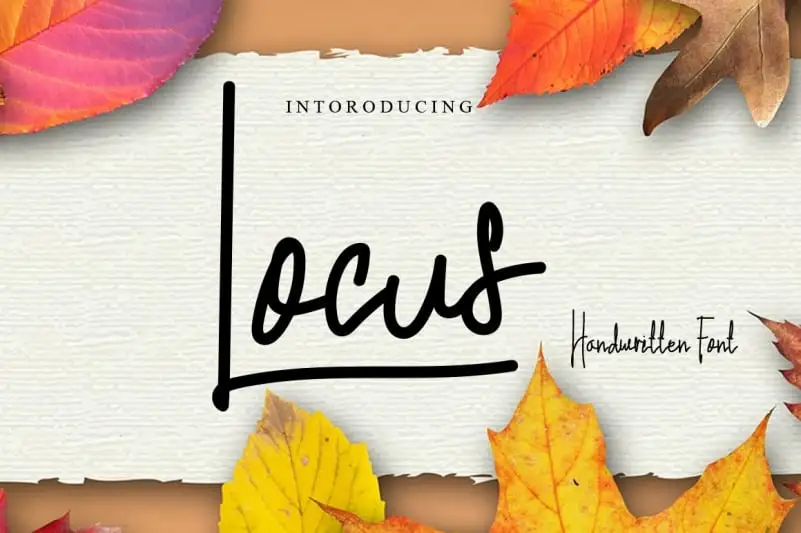
Locus Handwritten Font – Download Grátis
A Locus Handwritten Font é uma elegante escolha para aqueles que buscam uma fonte escrita a mão com um toque natural e fluído. Esta fonte é perfeitamente adaptada para ambientes digitais, sendo ideal para designers que desejam dar vida aos seus projetos digitais de forma atraente e única. Ela possui um equilíbrio entre simplicidade e impacto visual, tornando-a perfeita para destacar seu design ao invés de se perder no meio da multidão. Seja você criando cartazes, artigos em blogs ou até mesmo estampas de camisetas, a Locus Handwritten Font irá garantir que seu trabalho destaque-se, proporcionando um toque especial e pessoal a cada projeto.